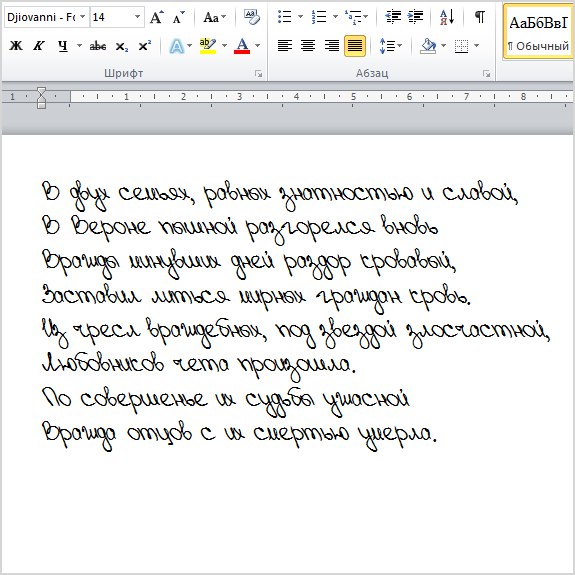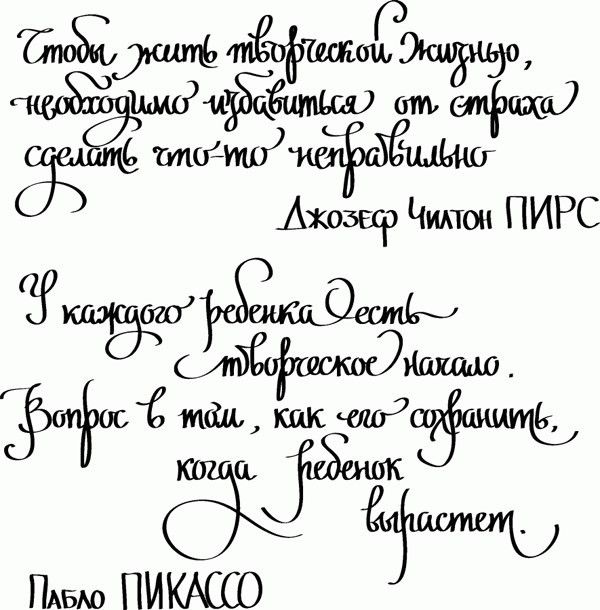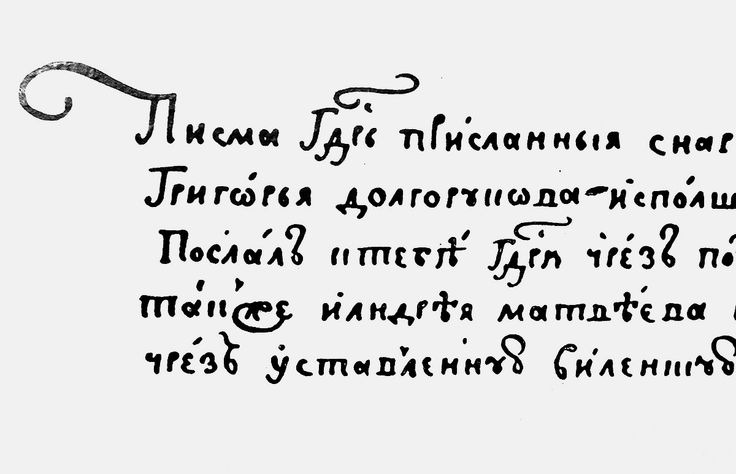
Шрифты для word кириллица рукописные: Рукописные шрифты — русские скачать бесплатно
Среди дизайнеров так и недизайнеров набирают популярности готовые шаблоны шрифтов. Их можно использовать для различных проектов, подобрав самый подходящий по стилю и начертанию. Из основных преимуществ:
- возможность настройки в Photoshop;
- поддержка языков;
- грамотно продуман кернинг — интервал между буквами в зависимости от их формы;
- несколько вариантов шрифтов в гарнитуре;
- несколько вариантов стилей.
Декоративный русский шрифт Acquest Script
Наклонный декоративный русский Adine Kirnberg
Модернисткий русский шрифт Agatha Modern
Классический декоративный шрифт Alexandra Script
Русский декор-шрифт Allegretto Script Two
Шрифт Andantino script в русской раскладке
Красивый декоративный шрифт Angelica
Арабский шрифт DS Arabic в русской раскладке
Шрифт Ariadna script с ярко выраженными заглавными
Русский шрифт Arkhive, сделанный под старину
Арт-шрифт ArtScript в русской раскладке
Жирный декоратинвый шрифт Asessor
Кириллический наклонный шрифт Astra
Еще один декоративный шрифт Aurora script
Шрифт Bickham Script One в кириллице
Вариация шрифта Bickham Script Three
Вариация шрифта Bickham Script Two
Кириллический шрифт Bolero script
Толстый русский шрифт Boyarsky
Каллиграфический русский шрифт Caligraph
Декоративный русский шрифт Calligraphia One
Декоративный русский шрифт Calligraphia Two
Аккуратный декоративный шрифт Cansellarist
Стильный декор-шрифт Carolina
Декоративный русский шрифт Cassandra
Русский шрифт Ceremonious One с вензелями
Русский шрифт Ceremonious Three с вензелями
Русский шрифт Ceremonious Two с вензелями
Аккуратный каллиграфический шрифтChampignon Script
Русский кириллический шрифт KB Chopin Script
Русский шрифт Connetable
Шрифт Copyist с завитушками
Рукописный Corinthia в русской раскладке
Жирный рукописный шрифт Corrida Bold
Жирный рукописный шрифт Corrida Cyrillic
Наклонный рукописный шрифт Cyrillic Brush
Строгий рукописный шрифт Cyrillic Ribbon
Русский шрифт Cyrillic Chancellor
Классический Decor CTT в кириллице